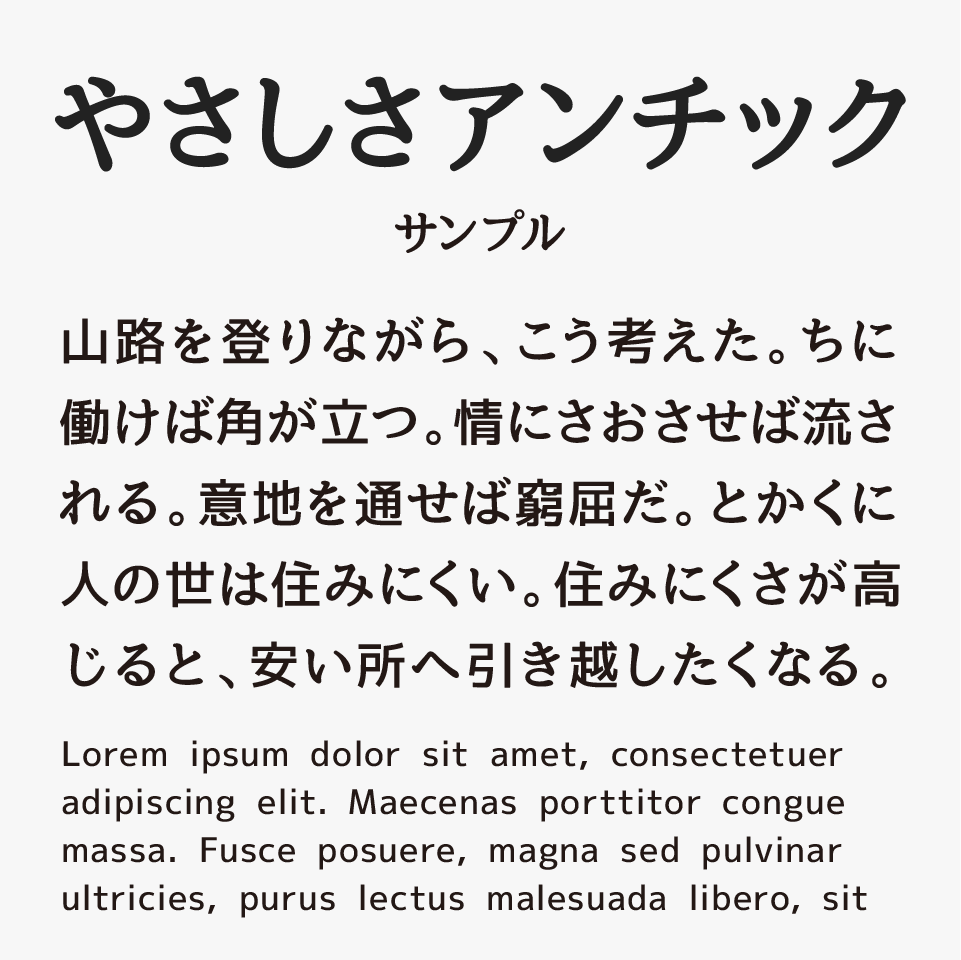
やさしさアンチック
やさしさアンチックは、少し太さのあるひらがなと漢字に統一感が高いデザインの漫画用フォントとして設計されてるフォントです。
アンチックフォントとは、漫画の吹き出しやセリフなどでよく使われる書体のひとつで、ひらがなは明朝体、漢字はゴシック体というように、異なるテイストを組み合わせて作られているフォントです。このような組み合わせの書体は、「アンチック体」と呼ばれています。
使い勝手が良く、マンガの吹き出し用として人気のあるフォントです。もちろん、吹き出し以外にも幅広いジャンルで活躍できるアンチック体フォントで、同人誌やコミック制作などにもぴったりです。
収録文字は、数字、アルファベット、記号、かな文字(ひらがな・かたかな)、教育漢字、常用漢字、第一水準漢字、第二水準漢字、その他主要な多言語が収録されています。